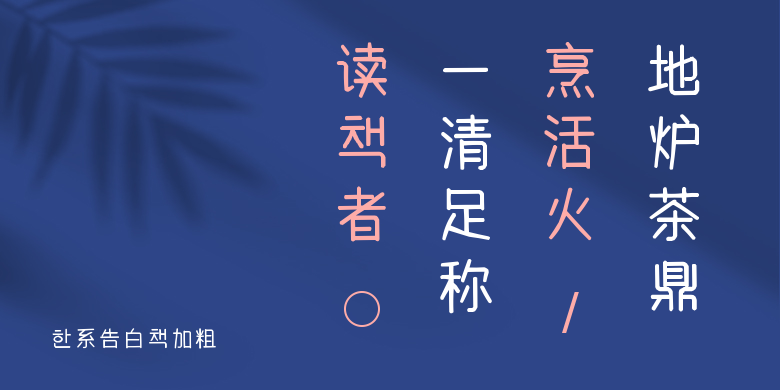
韩系告白书加粗
韩系告白书加粗,这款字体结构工整、笔画清晰,兼顾美观与易读性,适用于标题、正文、海报、包装、LOGO 等多种场景。字形优雅稳定,风格百搭耐看,适配日常排版与创意设计,让文字呈现更舒适、更具质感。韩系告白书加粗一笔一画,皆是细节,以均衡的比例、流畅的线条打造舒适视觉体验,字形端正大气,风格简约现代。无论是商业设计、品牌宣传还是日常排版,都能轻松驾驭,让文字更有格调与力量。韩系告白书加粗字体下载。